Была, осталась, видоизменилась…
История с продолжением
Не сглаживая углов…
Сглаживая углы…
Вместо заключения
История с продолжением
В иллюстративных примерах, которые были выбраны для предыдущей публикации (см. КомпьюАрт № 8’2008), фигурировал не вполне обычный, по меркам нынешней российской рекламной практики, ненасыщенный акцидентный шрифтовой материал. Необходимо отметить, что в рассматриваемом временном интервале в акцидентных задачах зачастую использовались и совсем иные функционалистские типографические конструкции, большинство из которых вошло в типографический обиход, начав не с наборных, а с титульных применений. Следуя линии, которая уже проводилась, до того как будет, по обыкновению, привлечен материал реминисцентного характера, попытаемся актуализировать сам предмет рассмотрения, а потому вначале уточним, о каком типографическом материале должна пойти речь. Для этого приведем последовательно пять чисто шрифтовых иллюстраций (рис.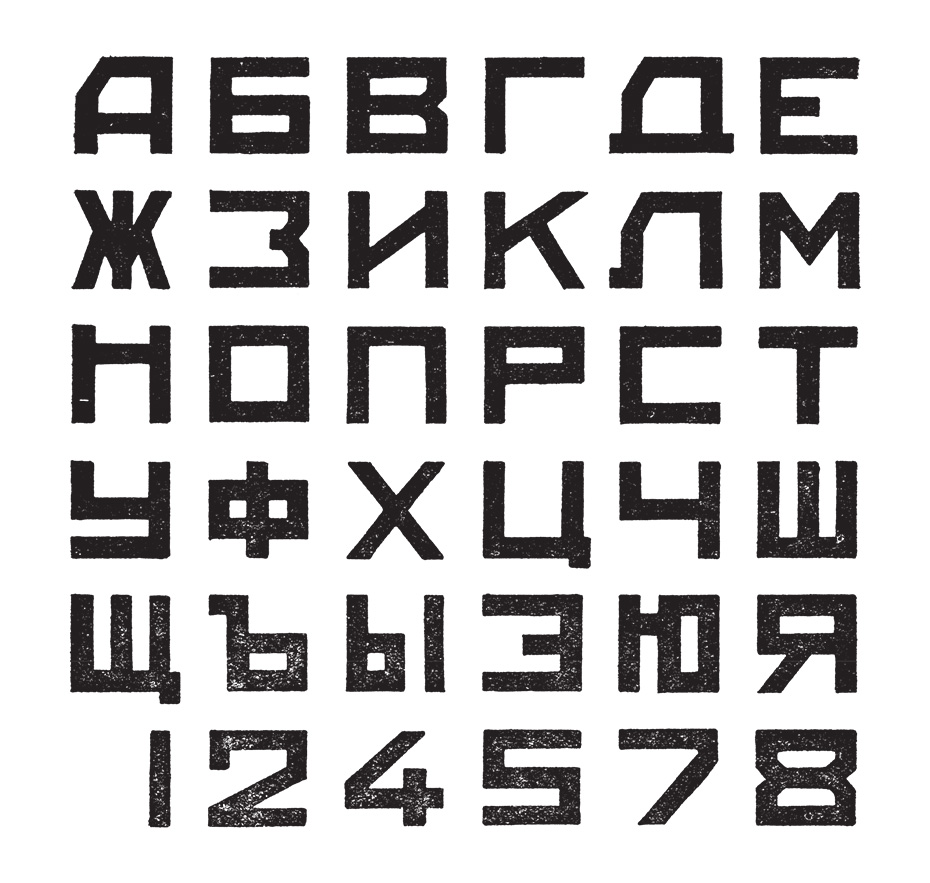
Первый пример (см. рис. 1) заслуживает того, чтобы его подробно прокомментировать, и вовсе не потому, что репродуцированные в нем шрифты разработал П.Реннер — один из признанных мэтров шрифтового искусства прошлого века. Приведенный здесь в двух верхних строках малоконтрастный функционалистский шрифт характерного угловатого рисунка цитируется во всех серьезных справочниках как одно из начертаний его знаменитой гарнитуры Футура. В зарубежных источниках он фигурирует как Futura Display, что в переводе означает «акцидентная, демонстрационная Футура». По стечению обстоятельств в тех отечественных публикациях, где писалось об этом шрифте, никто не задался вопросом, как так случилось, что сам Пауль Реннер включил в свои гарнитуры даже не одно, а два начертания, стилистически кардинально отличающихся от всех других. Кстати, второй из упомянутых шрифтов практически всем хорошо известен — это Futura Black.
Возможно, самое удивительное состоит в том, что для того, чтобы убедиться в этих стилевых различиях, не надо заниматься поиском комментариев даже самых маститых зарубежных аналитиков — достаточно здравого смысла и той подготовки, которую получают, например, студенты младших курсов в том же «Полиграфе». Для облегчения такого сопоставления в двух нижних строках примера процитировано близкое по насыщенности начертание Futura Bold. Отметим кратко, что, комплектуя свою гарнитуру, Реннер пытался создать своего рода универсальный набор шрифтоначертаний, который в будущем мог быть использован, по представлениям того времени, где угодно. Естественно, что он при этом не только базировался на своих знаниях, но и творчески обработал тот реальный графический материал, который к тому времени был накоплен в практике европейской рекламы. К сожалению, случилось так, что Futura Display в России пока не локализован. Это тем более досадно, поскольку акцидентные достоинства графики, которая реализована в этом шрифте, достаточно очевидны.
В следующей иллюстрации (см. рис. 2) приводятся два из четырех начертаний шрифта в названии, которого вновь фигурирует слово Futura. Создателем этой завершенной в 1955 году разработки, в которую входят также еще два курсивных начертания, является все тот же П.Реннер, который и дал ей тогда название Futura Steile.
В данном случае П.Реннер фактически обобщил те идеи, которые он воплотил вначале в шрифте Futura Display, сохранив при этом прежнюю угловатую стилистику. Вряд ли имеет смысл комментировать совершенно очевидные графические и прикладные достоинства этой гарнитуры. Стоит лишь упомянуть, что Реннер, фигурально выражаясь, стандартизировал этой своей разработкой 1956 года альтернативные варианты начертаний таких букв, как А, E, K, M, N и W, которые ранее использовались другими художниками от случая к случаю, главным образом в рекламных плакатах. Свидетельством популярности этих альтернативных начертаний могут быть многие образцы шрифтов, созданные в период своеобразного второго пришествия арт деко, которое, начавшись в конце 1950-х годов, активно продолжалось почти десять лет.
В третьей иллюстрации (см. рис. 3) представлен хорошо всем знакомый шрифт. На всякий случай напомним, что в этом примере фигурируют четыре из семи вариантов шрифтоначертаний гарнитуры Eurostyle, которую известный итальянский дизайнер А.Новарезе создал в 1962 году. Рисунок знаков этой гарнитуры во многом обобщает опыт многих плакатных работ, создававшихся в 1920-30-е годы, с той разницей, что тогда в них преобладало использование прописных букв. Обратим внимание на то, что в этой гарнитуре, наряду с двумя шрифтами нормальной ширины, присутствуют расширенные, суженные и даже компактные начертания. Этот шрифт хорошо известен у нас во многом потому, что вот уже почти полтора десятка лет неизменно фигурирует в составе популярного пакета CorelDRAW. К сожалению, в последнее время шрифты такого типа почему-то редко употребляются в отечественной рекламе, несмотря на то что остаются популярными в Европе и Северной Америке. Более того, шрифтовые дизайнеры, работающие в странах Запада, в последние годы создали немало достаточно широко востребованных в нынешней акцидентной практике геометризованных шрифтов, где в рисунке букв преобладают штрихи, идущие в вертикальном и горизонтальном направлении, причем для практики важно, что многие из этих разработок тяготеют к популярной стилистике хай-тек.
Уже в 90-х годах были созданы шрифты, выбранные для четвертой иллюстрации (см. рис. 4). В приведенном примере процитированы оба начертания гарнитуры Stenberg, которая была создана одним из известных отечественных дизайнеров шрифта Т.Сафаевым и которая вместе с другой его аналогичной разработкой с 1997 года присутствует в каталогах компании «ПараТайп». Многим известно, что шрифты подобного рисунка часто использовали в своих плакатах такие художники русского послереволюционного авангарда, как братья Стенберги и А.Родченко. Более того, в их работах применялись также шрифты, рисунок которых близок к прописным буквам ранее процитированной нами гарнитуры Eurostyle. Эти жестко геометризованные шрифты у нас до сих пор продолжают использоваться, причем это едва ли не единственная чисто российская шрифтовая разработка, которую почти сразу после ее создания лицензировала и ввела в свои каталоги такая известная шрифтовая фирма, как International Typeface Company (ITC).
В последней иллюстрации заявленной серии (см.
рис. 5) показана гарнитура Simpler, которая была разработана автором статьи в том же 1997 году для шрифтового авторского проекта «ТРИ-О-ГРАФ», входившего в состав пакета «Русский Офис». Так вышло, что из-за отсутствия государственной поддержки главный инвестор данного проекта — компания «Ай-Ти» работы над этим пакетом в самом начале 2000-х годов прекратила, однако его шрифтовой комплект до сих пор фигурирует среди широкодоступных ресурсов Интернета и продолжает использоваться в дизайнерской практике.
Применительно к последнему рисунку заявленной серии необходимо отметить, что основным в нем является первый недекорированный алфавитный фрагмент, в то время как второй просто является попыткой автора, памятуя о знаменитом логотипе фирмы IBM, ввести в современное пользовательское обращение один из популярных в 1930-х годах вариантов отделки. Строго говоря, данный шрифт не может быть непосредственно соотнесен с неконтрастными функционалистскими шрифтами точно так же, как, например, упоминавшаяся классическая разработка П.
Возвращаясь к тезису, высказанному в самом начале раздела, применительно к пяти рассмотренным примерам необходимо вновь повторить, что акцидентные возможности такой графики у нас в обиходной практике дизайна пока оказываются не столько недооцененными, сколько недоиспользованными. Поэтому приведем еще несколько примеров (рис. 6-10) как высокоуровневых, так и вполне обыденных применений такого рода шрифтов.